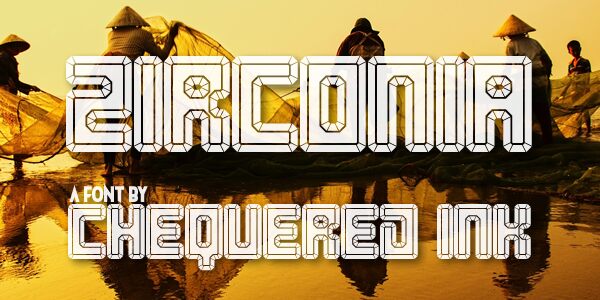
Zirconia to darmowy, fasetowany krój pisma typu display, zbudowany z szerokich, obrysowanych pociągnięć i ostro ciętych rogów. Powtarzające się kątowe łączenia, wpuszczane refleksy i podziały przypominające klejnoty sprawiają, że litery przypominają fazowany metal lub kryształowe formy, mając bryłowatą sylwetkę, która wydaje się zarówno futurystyczna, jak i zainspirowana grami arcade.
Może przekształcić tytuł gry w coś będącego po części logo, a po części zilustrowanym interfejsem. Te same zaprojektowane fasetki pasują do plakatów science-fiction, opakowań muzyki elektronicznej i gadżetów esportowych, gdzie napisy mogą nawiązywać do płyt pancerza, oszlifowanych kamieni szlachetnych lub grafiki low-poly, zamiast zachowywać się jak neutralny krój.